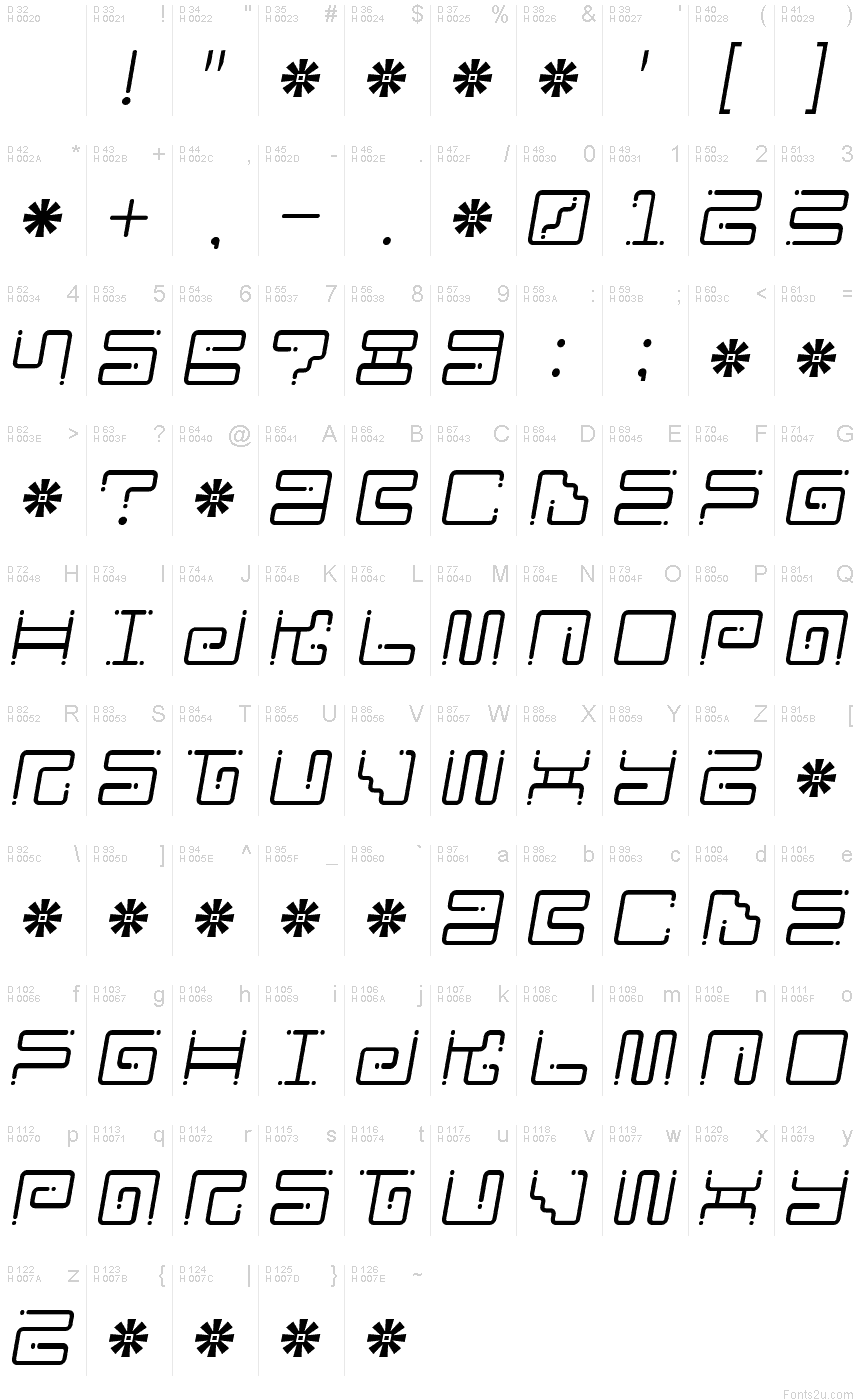
Iron Lounge Dots 2
Iron Lounge Dots 2 di Jakob Fischer è un font display gratuito dallo stile futuristico e groovy. Le sue lettere sembrano tubi al neon fluidi, che si piegano in curve rilassate e punteggiate da punti giocosi, come minuscoli LED. Gli angoli arrotondati e lo spessore costante conferiscono un aspetto tech-lounge lucido: un mix tra una sala giochi rétro e un’insegna di un locale sci-fi.
Con Iron Lounge Dots 2, puoi dare carattere immediato a poster musicali, flyer per club o festival, copertine di libri di fantascienza, loghi di gaming, grafiche per Twitch e apparel design. La spaziatura aperta mantiene la leggibilità anche nelle grandi dimensioni, dove i dettagli puntinati risaltano davvero. Abbina questo font gratuito a un sans serif geometrico pulito per il testo e lascia che Iron Lounge Dots 2 si occupi dei titoli.